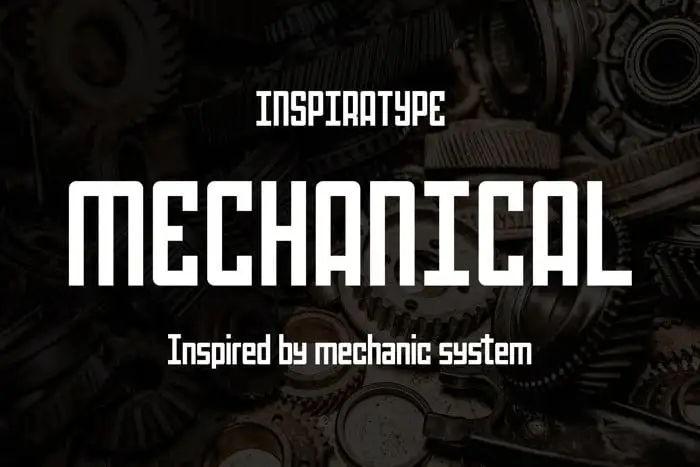
Mechanical Sans Serif Font – Fonte Grátis
Mechanical Sans Serif Font
A ‘Mechanical Sans Serif Font’ é uma opção única para designers que buscam uma fonte visualmente atraente e moderna, inspirada na esportes. Com seu formato condensado e sans-serif, esta fonte ganha um toque esportivo que é perfeito para projetos criativos. Ela traz uma ampla variedade de opções no campo da tipografia abrangendo letras maiúsculas e minúsculas, números, pontuações e muito mais. O OpenType alternativas, ligaturas comuns e também swashes adicionais oferecem um espaço ilimitado para personalizar seus designs. Ainda que seja uma fonte de exibição, seu uso é praticamente limitado apenas pelos projetos tipográficos — como logotipos, materiais do escritório, panfletos, roupas e embalagens. Seu formato condensado a torna ideal para criar texturas impactantes em qualquer aplicação visual onde seja necessário um design visual mais moderno e distante. Assim, se você está procurando por uma fonte que combine funcionalidade com estilo, esta é a escolha perfeita.